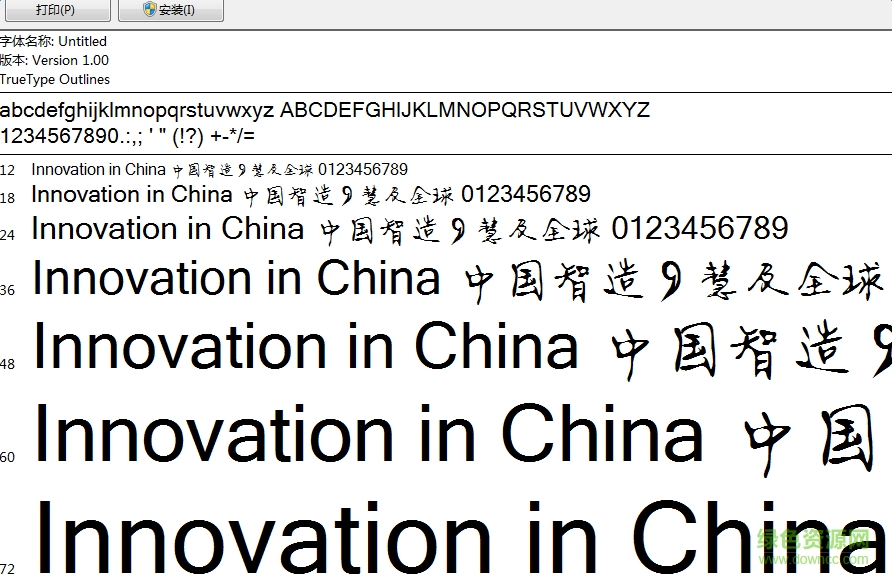
軟件介紹 軟件標(biāo)簽: 其他字體 字體 時裝靜蕾鋼筆體字體是一款極具個性的鋼筆字體,可以廣泛應(yīng)用于廣告設(shè)計、宣傳海報、ppt、影視制作以及任何使用文字的領(lǐng)域,有需要的朋友可以免費下載收藏。字體安裝方法方法一:控制面板/字體/文件/安裝新字體;方法二:直接將字體復(fù)制到C:\WINDOWS\Fonts。方法三:針對win7系統(tǒng),用戶只需選中字體右鍵安裝即可。注意事項本站所有字體資源僅供個人學(xué)習(xí)與參考,如需商業(yè)使用請到相關(guān)官網(wǎng)授權(quán)。 軟件截圖 上一張下一張(1 / 1) 安裝詳細(xì)截圖 猜你喜歡 時裝字體 鋼筆字體 時裝字體 時裝字體是一種很有特色的電腦字體,不僅寫出來的字形美觀,效果也很不錯,因此使用范圍也比較廣,特別是用于廣告設(shè)計、藝術(shù)設(shè)計等方面都是很不錯的,小編為大家?guī)頃r裝字體大全和打包,歡迎大家來綠色資源網(wǎng)下載使用。 查看更多>> 時裝斑馬魏 10.82M/中文/10.0/下載 時裝滾邊體 11.71M/中文/10.0/下載 時裝毛邊體 24.41M/中文/10.0/下載 時裝豆點細(xì)圓體 3.12M/中文/10.0/下載 時裝扭動體 3.74M/中文/10.0/下載 時裝揪心體 1.91M/中文/10.0/下載 鋼筆字體 鋼筆字體是設(shè)計領(lǐng)域經(jīng)常用到的字體,鋼筆字體具有鮮明的個人特征,風(fēng)格多樣,深受廣告設(shè)計、平面設(shè)計師的喜愛,除了一些手寫鋼筆字體,還有正楷、行書類的鋼筆字字體,為設(shè)計師們提供了豐富的字體形式,綠色資源網(wǎng)也有很多鋼筆字體下載和鋼筆字體包,需要的可以看一看 查看更多>> 鋼筆書法軟件手機版 103.96MB/中文/10.0/v2.2.0 安卓版下載 鋼筆之家 4.83M/中文/10.0/v1.0.2 安卓版下載 鋼筆手寫字體免費 11.71M/中文/1.2/下載 鋼筆書法入門基知識 31.79M/中文/5.0/v6.3.1 安卓版下載 浮生體 1.92M/中文/5.0/下載 伯樂鋼筆行書字體 3.53M/中文/6.6/下載 其他版本下載 標(biāo)題 大小 更新日期 下載 下載地址 電腦版 時裝靜蕾鋼筆體 點擊報錯 軟件無法下載或下載后無法使用,請點擊報錯,謝謝! 關(guān)閉報錯反饋 請描述您所遇到的錯誤,我們將盡快予以修正,謝謝! *必填項,請輸入內(nèi)容 本類最新 dreamweaver字體庫 首爾南山體字體 v1.06 官方版 潮字社風(fēng)云簡ttf 潮字社凌渡鯤鵬簡體字體 潮字社曾玉波手書簡字體 微博慧心字體 相關(guān)文章 Photoshop字體安裝使用方法和技巧 如何解決“無法新增字體”問題 Win 7系統(tǒng)安裝字體方法 網(wǎng)頁字體大小設(shè)置方法 怎么改網(wǎng)頁字體大小 在Linux系統(tǒng)中安裝字體的幾種方法 windows7字體顯示問題:打開某些程序的時候顯示的是亂碼 用戶評論 熱門評論 最新評論 發(fā)表評論 查看所有評論(0) 昵稱: 請不要評論無意義或臟話,我們所有評論會有人工審核. 字?jǐn)?shù): 0/500 (您的評論需要經(jīng)過審核才能顯示)